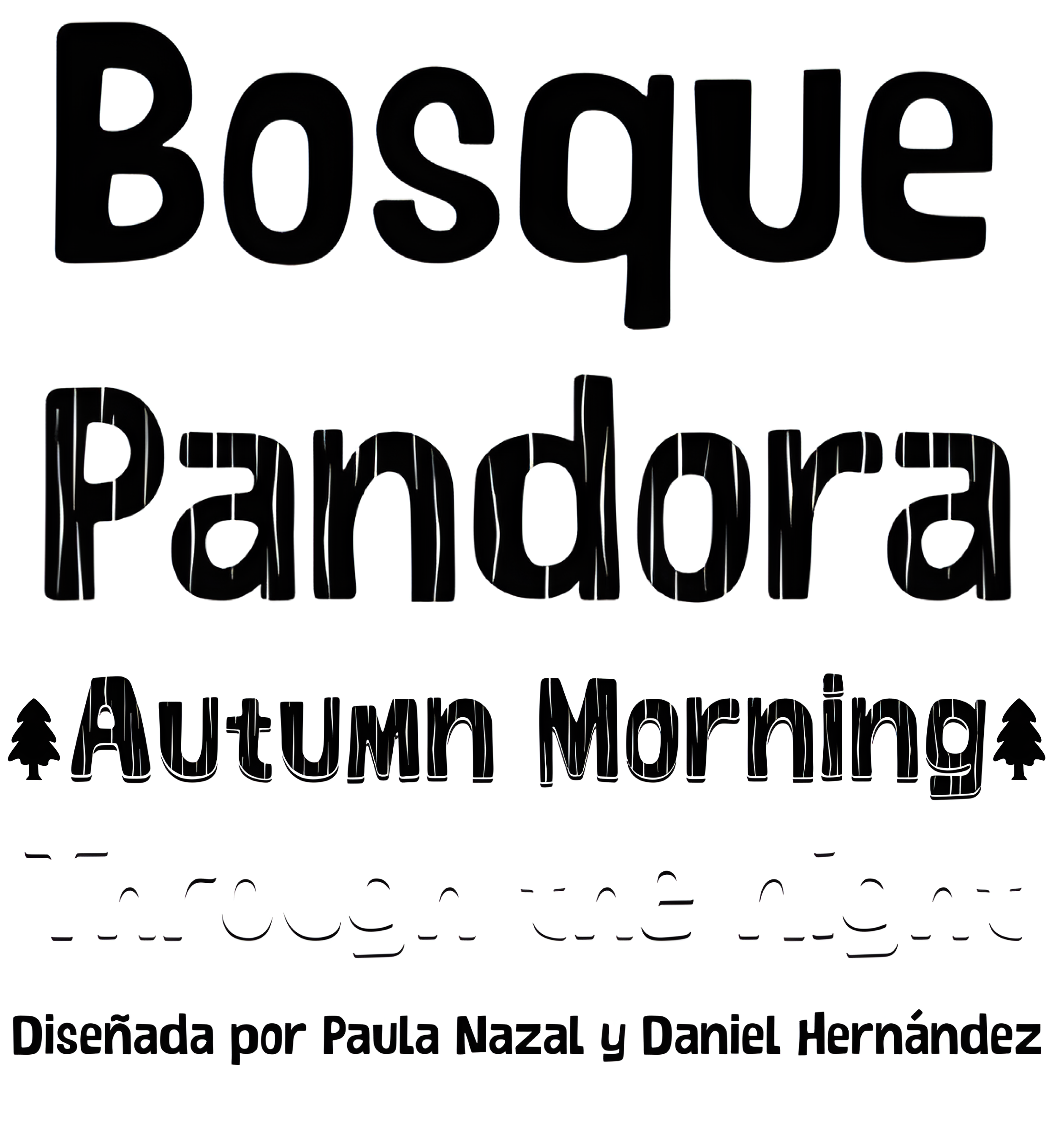
Bosque
| Año | 2012 |
| Créditos | Paula Nazal Selaive, Daniel Hernández |
| Descripción | Bosque es un tipo de letra diseñado por Paula Nazal y Daniel Hernández. Pertenece al estilo handmade, es áspera y cruda con bordes suaves. Tiene 6 variantes: Normal, Wood, Shadow, Wood Shadow, Dingbats y Shadow One, esto le da una gran versatilidad. Posee un amplio conjunto de caracteres, ligaduras y algunos alternativos. |
| Clasificación | Títulos, Dingbats |
| Familia(s) | Regular, Shadow, Wood, Wood Shadow, Dingbats, Shadow One |
| Estilos | 6 |
| Set | Especializado |